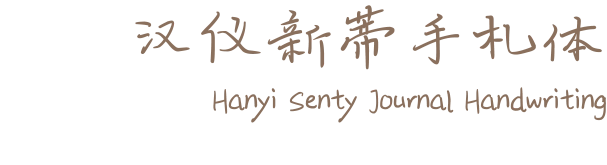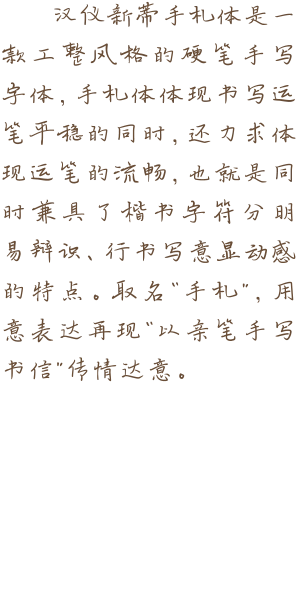
汉仪新蒂手札体 Hanyi Senty Journal Handwriting
作者:王维 涵盖字符:简繁中文10000+
汉仪新蒂手札体是一款工整风格的硬笔手写字体,手札体体现书写运笔平稳的同时,还力求体现运笔的流畅,也就是同时兼具了楷书字符分明易辩识、行书写意显动感的特点。取名“手札”,用意表达再现“以亲笔手写书信”传情达意。